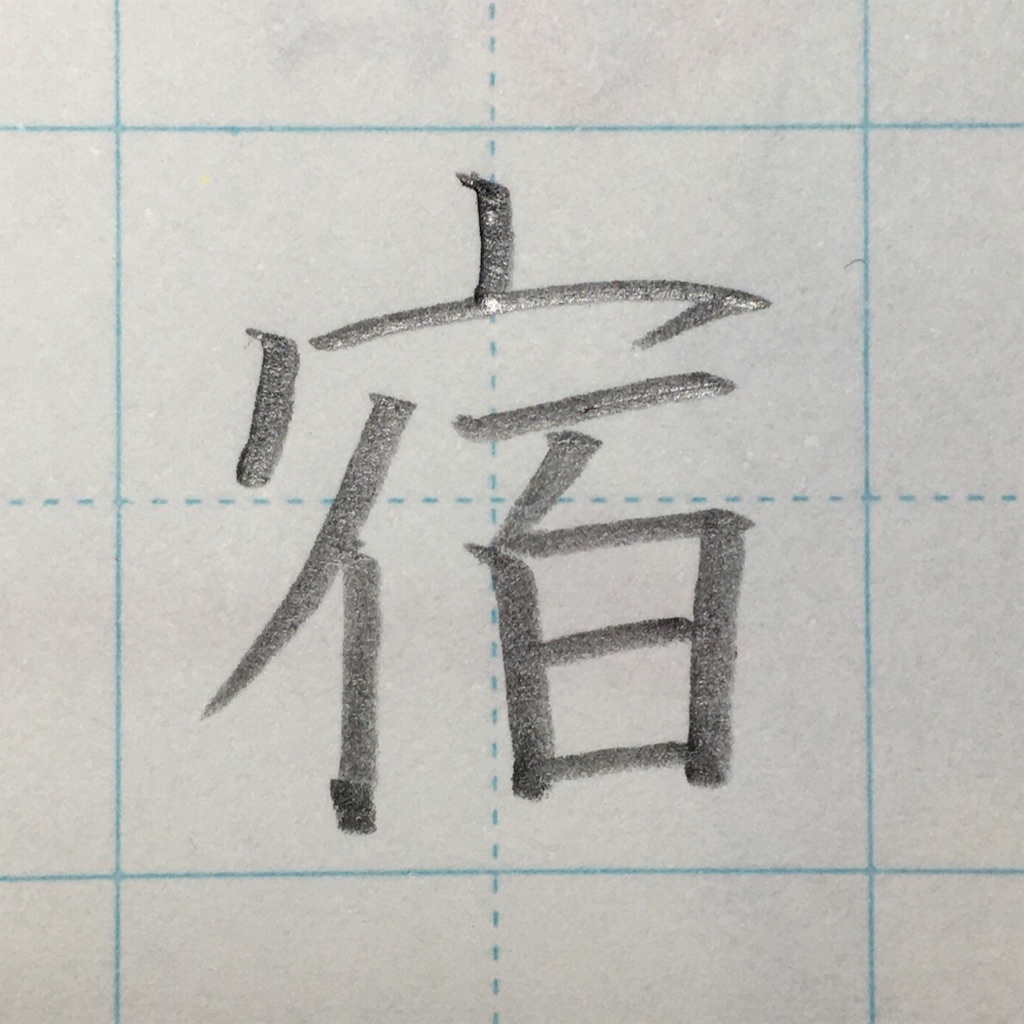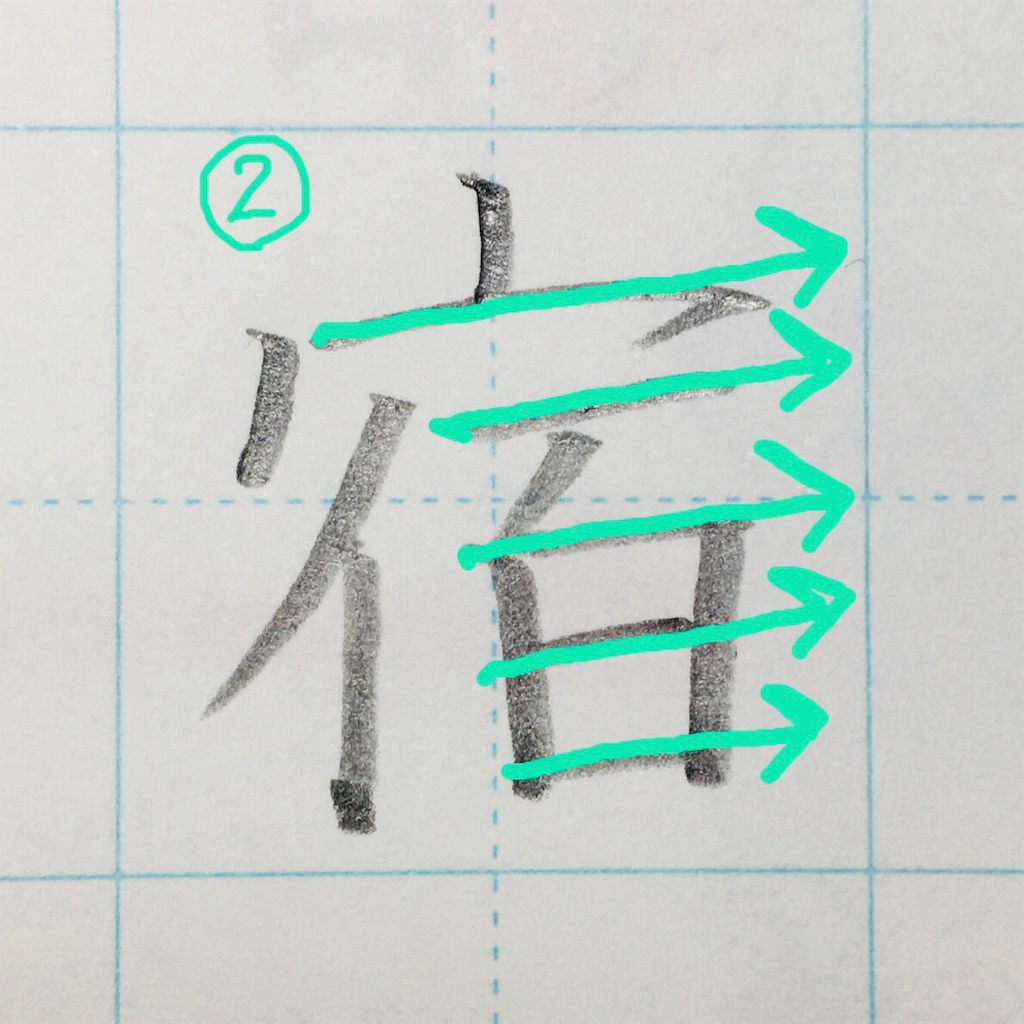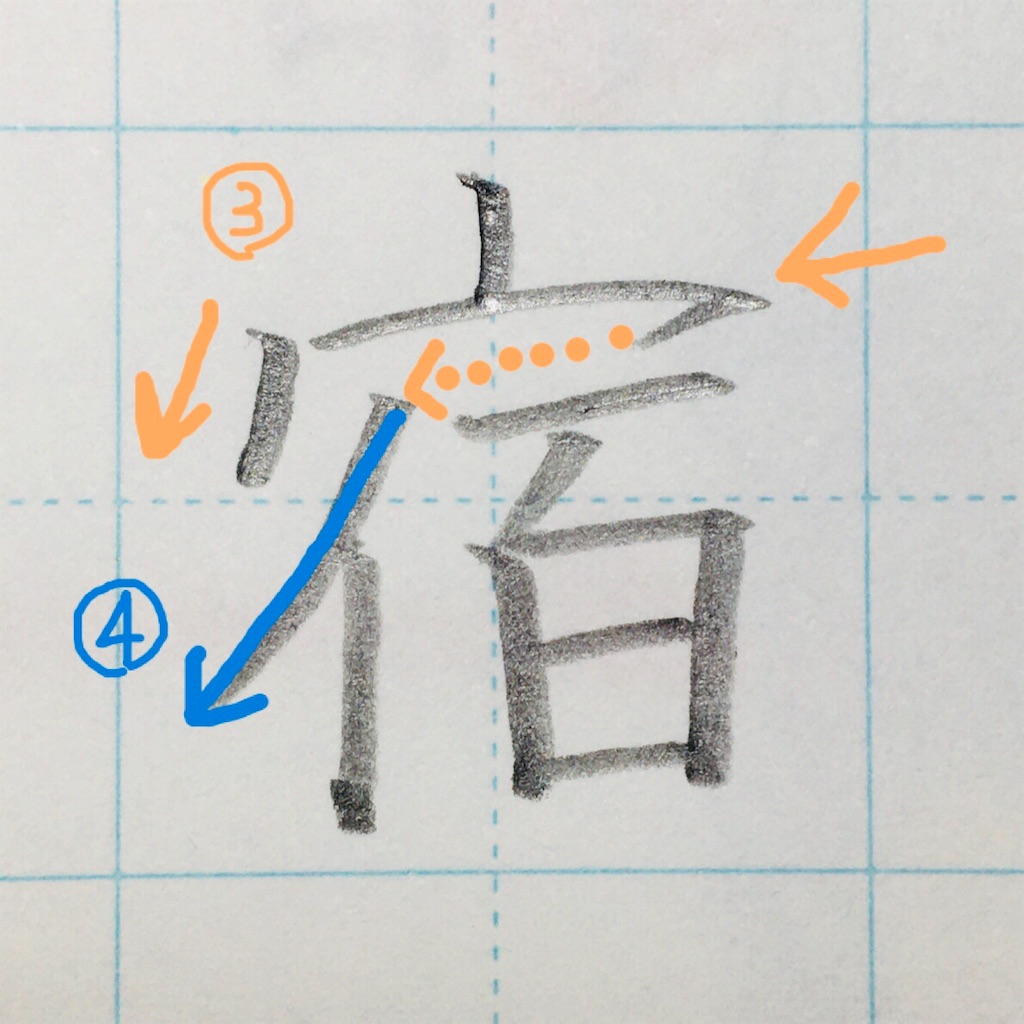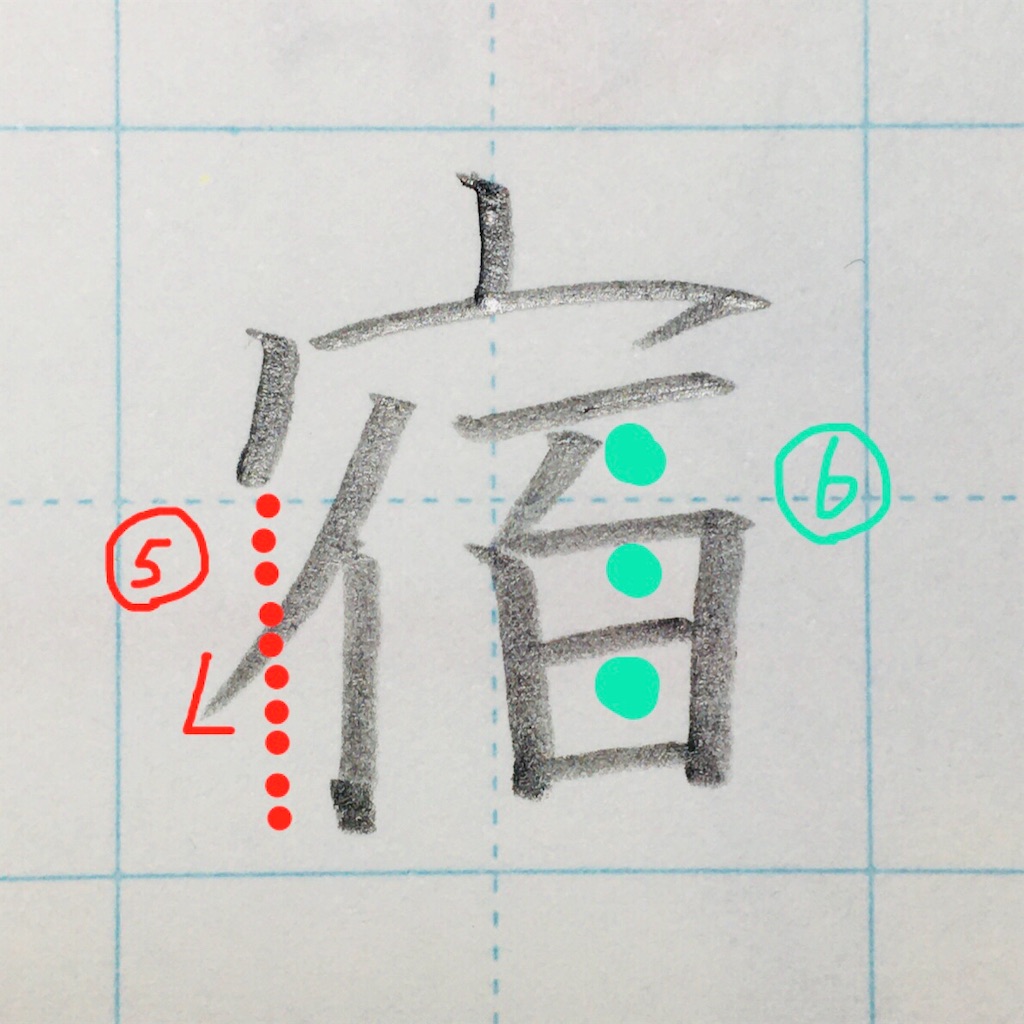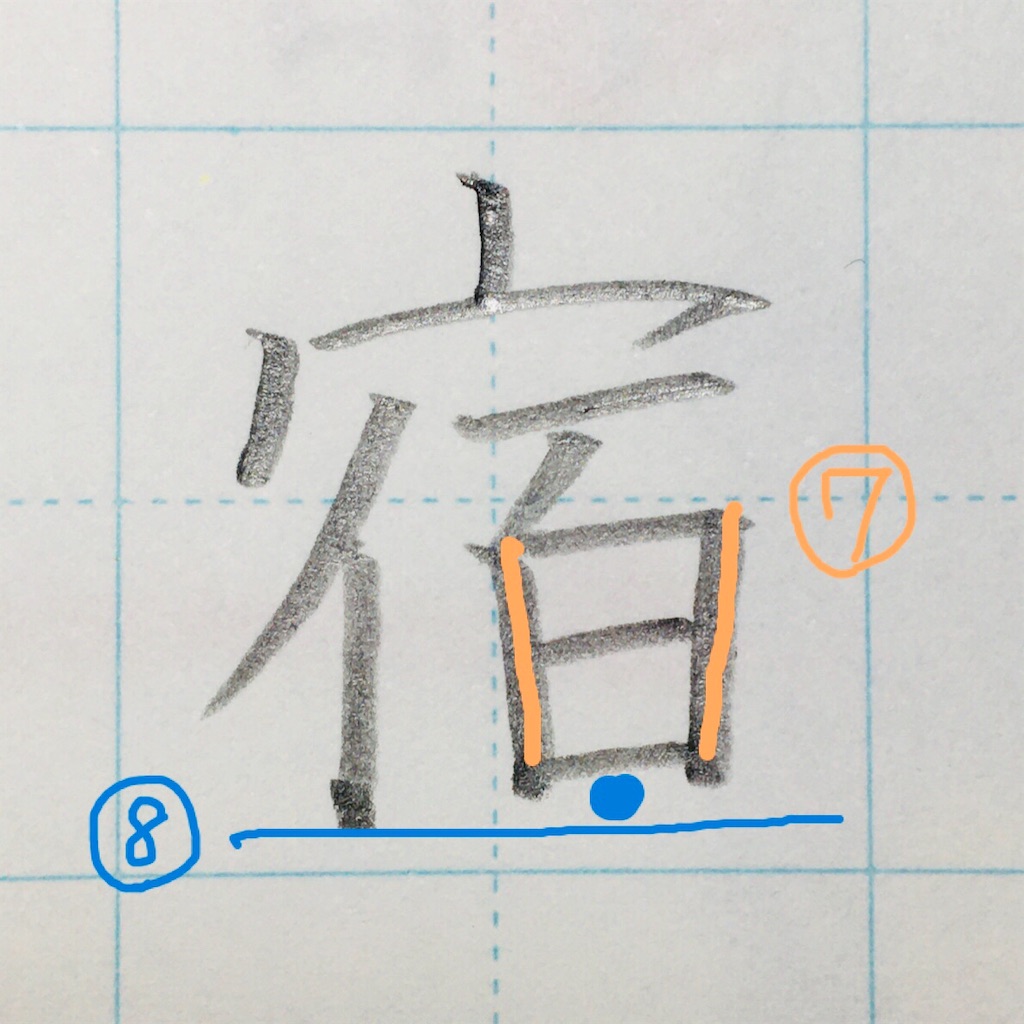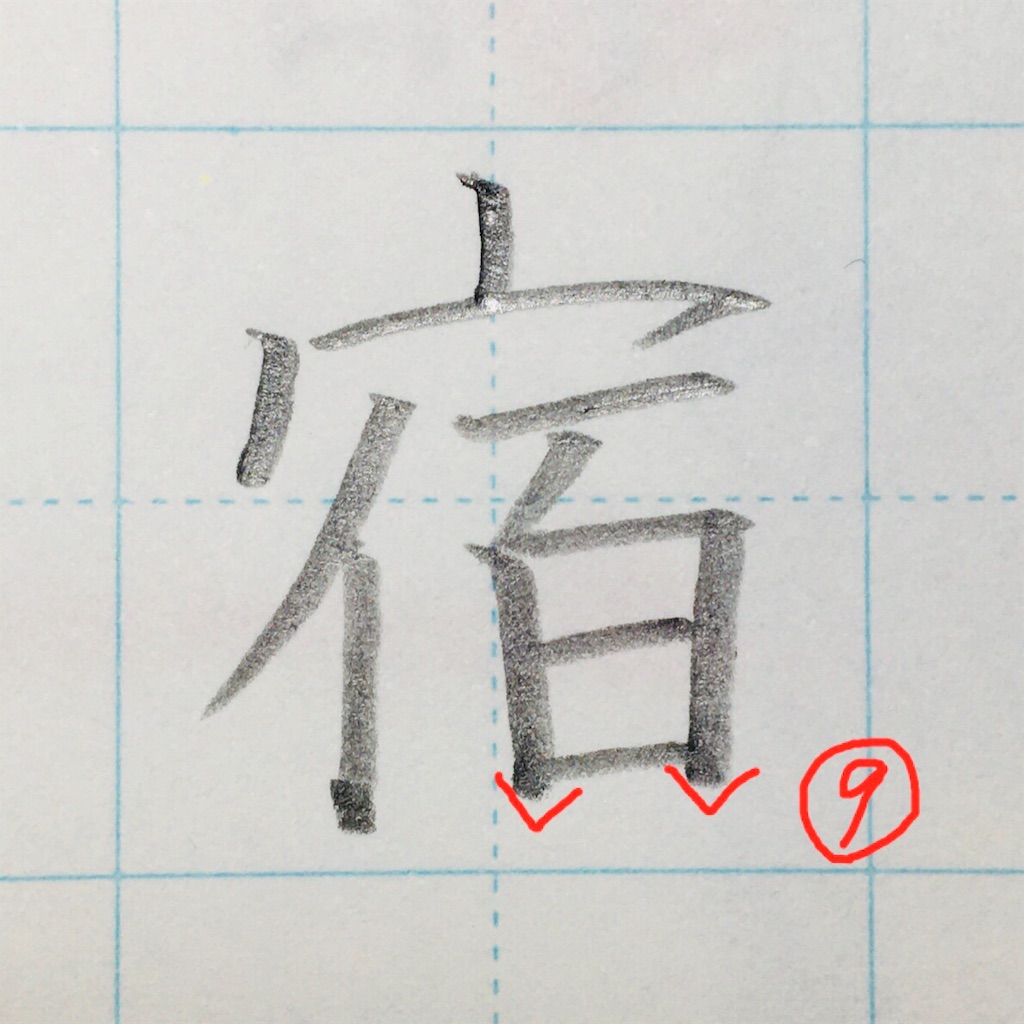
今回は「宿」のきれいな書き方を解説します。
「宿」のきれいな書き方
「宿」の書き方ポイント
①●部分を中心に配置する。
(白紙に書く場合は、1画目の点を基準に中心が通るように意識する。)
②横画は右上がりに揃える。
これがしっかりできると、洗練された文字に‼
③【うかんむり】
2画目は、外に向けて斜めにする。
3画目は、内側にシュっと払う。
(次の画に向かう気持ちで書くと◎)
④30°くらいで払う。
⑤「うかんむり」よりも、少し外に出る。
⑥間を等しく。
⑦ほんの少し、内に入れる。(同じ角度で)
⑧「イ」よりも、「百」が少し上で終わる。
⑨「縦」が出る。
⭐︎1画目の点は、斜め(45°位)でもOKです(^o^)お好みで♩